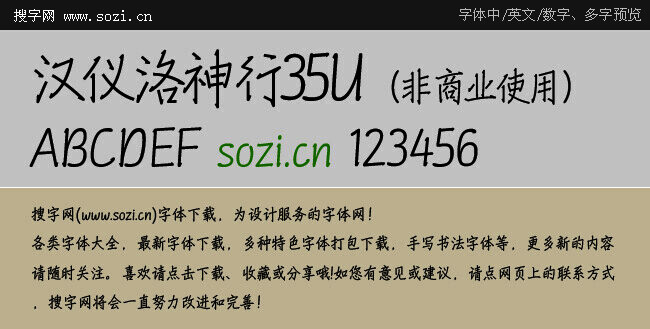
漢儀洛神行35U
搜字網(wǎng)給大家提供一款漢儀洛神行35U中文字體下載,漢儀洛神行取意趙孟頫行書(shū)《洛神賦》卷,行中兼楷,在字形結(jié)構(gòu)上尋求“竦輕軀以鶴立,若將飛而未翔”的意境,結(jié)合現(xiàn)代等線的筆畫(huà)設(shè)計(jì),保留行楷的流暢瀟灑而減弱古舊氣息。漢儀洛神行的字形偏長(zhǎng),中宮略小而筆畫(huà)舒展,挺拔如鶴立。重心平穩(wěn),字形略帶書(shū)寫(xiě)的自然傾斜,呈現(xiàn)“若將飛而未翔”之勢(shì)。適用于畫(huà)冊(cè)設(shè)計(jì)、海報(bào)設(shè)計(jì)、包裝設(shè)計(jì)等場(chǎng)合使用。(本字體為個(gè)人非商用版,如需要商用請(qǐng)聯(lián)系漢儀公司購(gòu)買(mǎi)版權(quán))